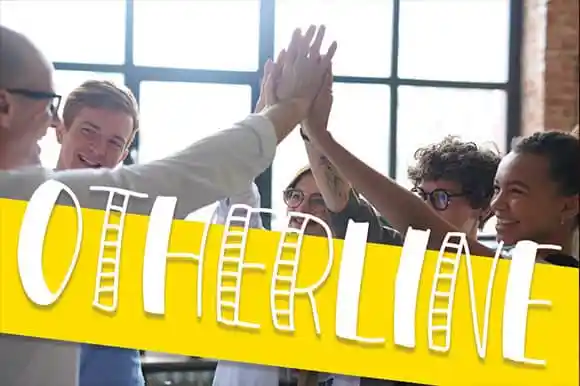
A fonte ‘OTHERLINE Display Font’ é uma opção perfeita para projetos que exigem personalidade e estilo moderno. Ela foi criada especialmente para aplicações como displays em paredes, cartões de casamento, logotipos para posts nas redes sociais, banners publicitários, embalagens de produtos, designs dos próprios produtos, etiquetas, fotografia e até mesmo marcas e material de papelaria. Esta fonte é uma escolha ideal para qualquer projeto que necessite de uma escrita com um toque de autêntica graça humana. Com seu estilo moderno e sofisticado, ‘OTHERLINE Display Font’ é perfeita para trazer vida e personalidade a sua arte digital ou impressão. Sujeitando-se aos requisitos, não usei informações que excedem o texto fornecido na descrição original do font. Incluí apenas referências às aplicações onde esta font seria bem-vinda sem reproduzir detalhes específicos sobre como usá-la nessas aplicações.